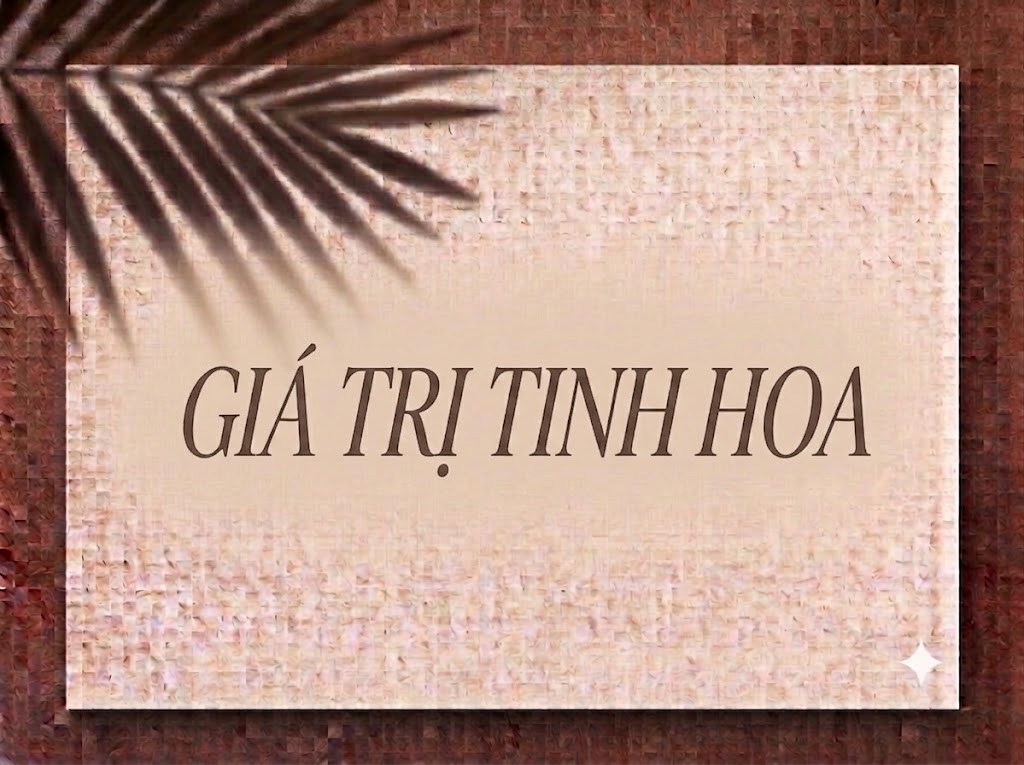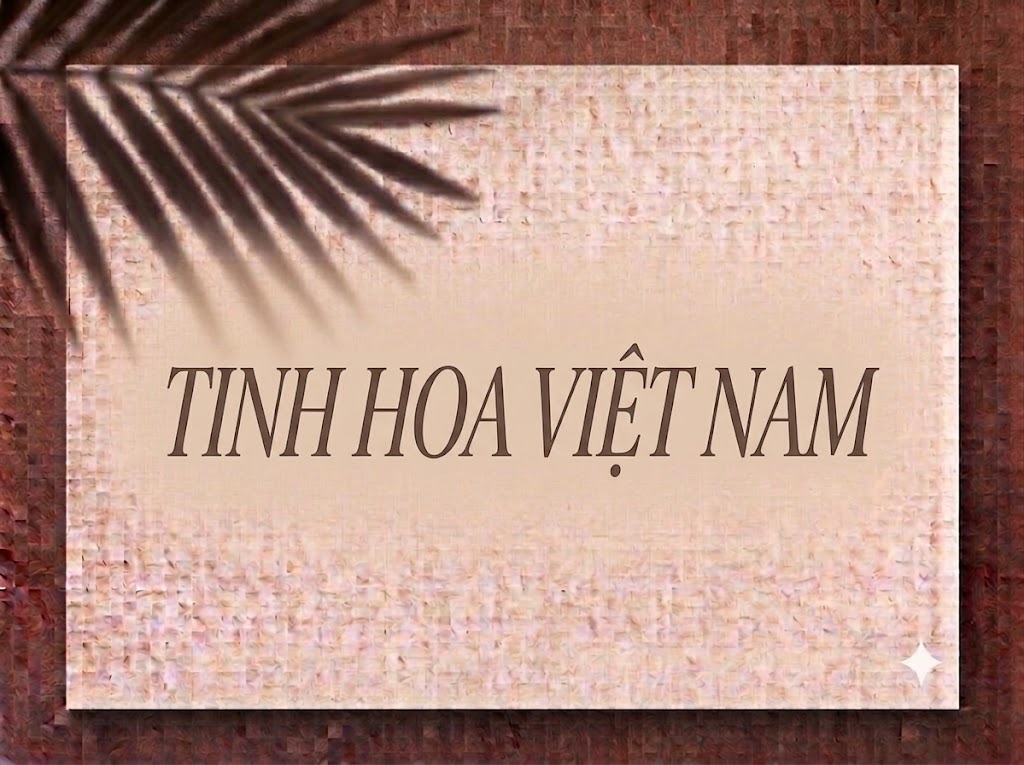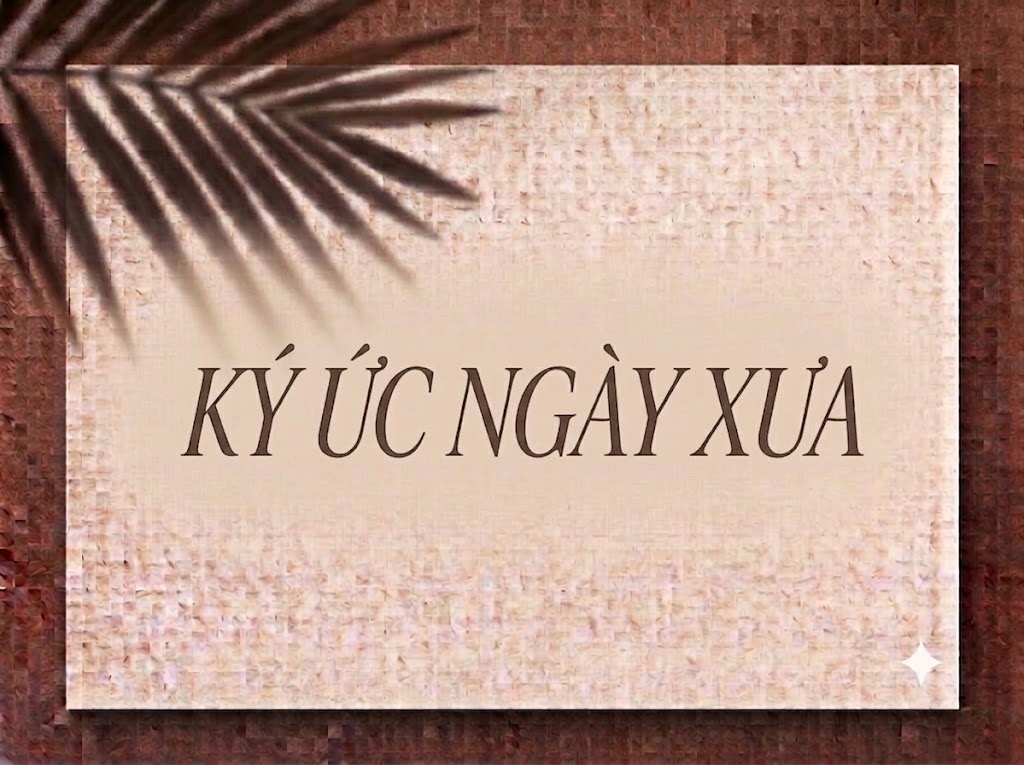
1FTV VIP Bonsad
Trong xu hướng thiết kế đồ họa hiện đại và truyền thông hình ảnh cao cấp, những bộ chữ hiển thị (display font) mang dáng dấp kiến trúc và Art Deco luôn là chìa khóa tạo nên sự khác biệt. Nhờ phom dáng cao ráo, các nét cắt hình học phá cách và sự tối ưu diện tích chiều ngang, kiểu chữ này giúp dòng tiêu đề vừa tiết kiệm không gian lại vừa bật lên sự sang trọng, độc bản.
Nếu bạn đang tìm kiếm một phông chữ không chân vừa thanh thoát, vừa có những đường nét góc cạnh đầy tính nghệ thuật cho bìa tạp chí, logo hay tiêu đề video ngắn, font 1FTV VIP Bonsad chính là lựa chọn rất đáng trải nghiệm.
Giới thiệu về font 1FTV VIP Bonsad
Font 1FTV VIP Bonsad là bộ chữ hiển thị mang phong cách hình học cao ráo (condensed geometric display), kết hợp giữa nét đẹp thanh lịch của nghệ thuật kiến trúc đương đại và sự hiện đại của thiết kế kỹ thuật số:
Tên phông chữ: 1FTV VIP Bonsad
Đặc điểm nổi bật của phong cách thiết kế VIP Bonsad
Sức hút thị giác của font 1FTV VIP Bonsad nằm ở phom dáng vươn cao cùng các chi tiết tạo hình phá cách kịch tính:
Phom dáng condensed vươn cao: Cấu trúc chữ thuôn dài theo chiều dọc giúp bạn dễ dàng chèn những câu tiêu đề nhiều từ vào khung hình mà vẫn giữ được cỡ chữ lớn, nổi bật.
Chi tiết gạch nét hình học độc đáo: Điểm đắt giá của VIP Bonsad nằm ở các góc vắt xiên và điểm giao nét lạ mắt ở các ký tự như A, M, N, W, K. Sự biến điệu này mang đến vẻ đẹp vừa mang tính Art Deco cổ điển, vừa đậm chất tương lai (futuristic).
Thiết kế đồng bộ, thanh thoát: Độ chênh lệch nét nhẹ nhàng cùng không gian nội tại chữ thông thoáng giúp câu từ luôn giữ được sự ngăn nắp và tinh tế khi đứng cạnh nhau.
Khoảng cách giữa các chữ (kerning) và độ giãn dòng được căn chỉnh chuẩn xác, giúp các ký tự dáng cao khi đứng sát nhau không bị chồng dính hay gây ngột ngạt.
Tích hợp trọn vẹn bộ chữ cái, dãy chữ số 0-9 phom dáng thanh lịch cùng bộ ký tự đặc biệt, dấu câu thông dụng.
Bản Việt hóa chuẩn chỉnh giúp bạn hoàn toàn yên tâm thiết kế các văn bản tiếng Việt có dấu mà không gặp lỗi nhảy font hay mất ký tự.
Hình ảnh demo thực tế của font 1FTV VIP Bonsad
Khả năng hiển thị của phông chữ này được tối ưu rất tốt trên nhiều tỷ lệ kích thước khác nhau:
Kích thước nhỏ (12pt – 24pt): Nhờ cấu trúc nét mảnh rành mạch, các câu chữ và dãy số vẫn hiển thị rõ ràng, thẳng hàng trên các giao diện màn hình di động.
Kích thước lớn (36pt – 72pt): Đây là đất diễn ấn tượng nhất để 1FTV VIP Bonsad phô diễn toàn bộ sự cao ráo, sang trọng và nét cắt hình học phá cách, tạo tác động thị giác mạnh mẽ cho các dòng headline chính.
Ứng dụng trong thiết kế đồ họa và làm video
Sở hữu nét cá tính kiến trúc và độc đáo, font 1FTV VIP Bonsad mở ra không gian ứng dụng vô cùng phong phú:
Video ngắn (TikTok, Reels, Shorts): Dáng chữ thuôn dài rất hợp với khung hình đứng tỷ lệ 9:16. Nó giúp bạn thoải mái chèn các cụm từ khóa chính hay giật tít dài ở đầu video mà không lo tràn viền hay che khuất chủ thể.
Ảnh thu nhỏ YouTube (Thumbnail): Lựa chọn tuyệt vời cho các kênh làm nội dung về kiến trúc, thiết kế nội thất, thời trang, review đồ công nghệ cao cấp hoặc nghệ thuật nhờ độ nhận diện trực diện.
Thiết kế bìa tạp chí, Lookbook và Poster: Hoàn hảo cho các ấn phẩm truyền thông thuộc lĩnh vực thời trang thiết kế, triển lãm mỹ thuật, dự án bất động sản hay sự kiện âm nhạc hiện đại.
Nhận diện thương hiệu cá tính: Thích hợp làm logo dạng chữ khối, menu nhà hàng hay khách sạn cao cấp, bao bì sản phẩm và ấn phẩm quảng cáo cho các thương hiệu phong cách.